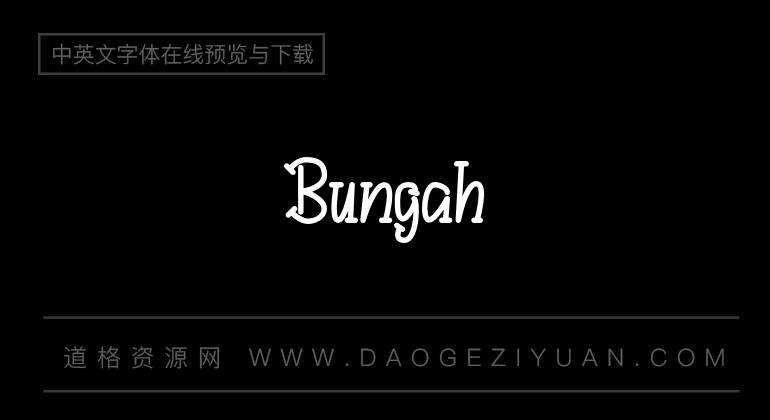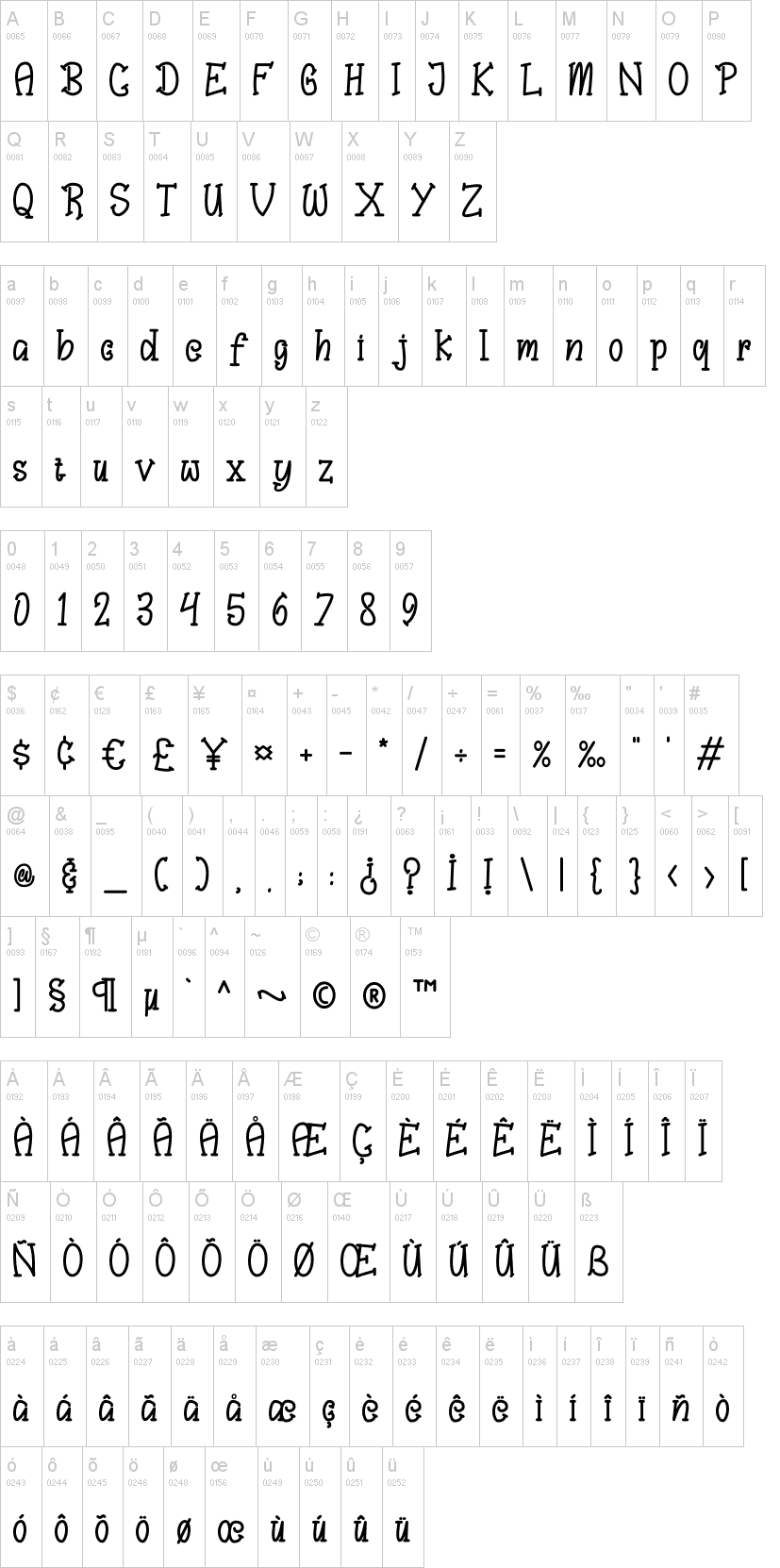
Bungah
Bungah 字体是一种拉丁文字体,由英国设计师 James L. Montalbano 创作。它具有现代感,具有优雅的线条,它的字体特点是细腻、优雅、现代、清新。它可以用于设计标题、标签、标语等,也可以用于文章、书籍、卡片等。Bungah 字体可以帮助您展示您的设计作品,让您的作品更加精致、优雅。
Bungah是一款非常不错的手写艺术字体,具有很好的视觉感,适合于文化类的宣传设计、商业类品牌的广告和产品包装设计以及个性化文字排版等较多场景。